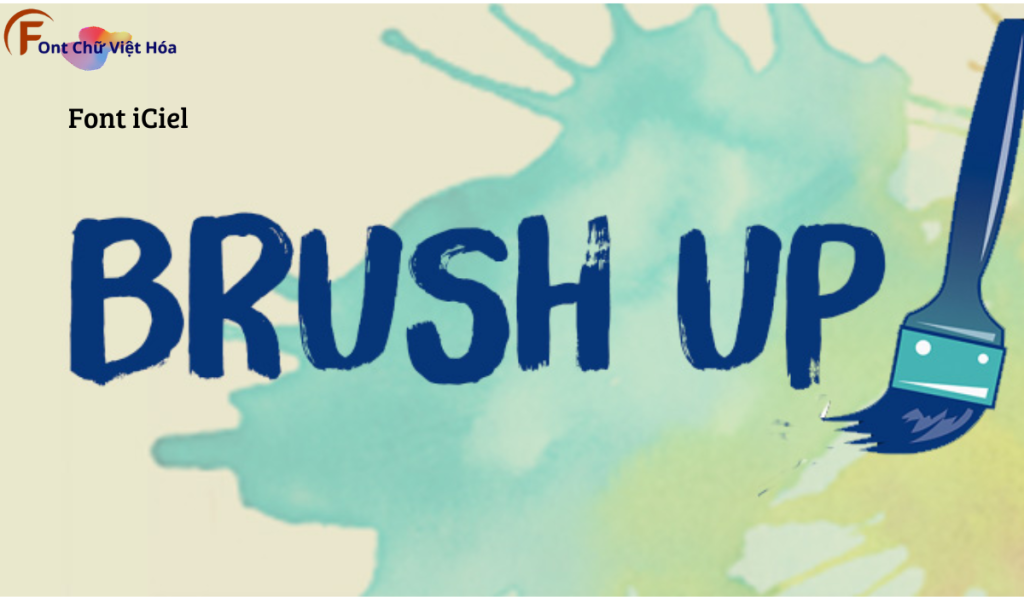
Font iCiel Brush Up Việt Hóa
Tác giả: iCiel Brush Up
Bộ Font: iCiel
Kiểu chữ: Chữ thảo
Font iCiel Brush Up Việt Hóa, thuộc bộ font iCiel, là font chữ thảo hiện đại, nổi bật với các nét chữ vẽ tay độc đáo và độ dày đa dạng. Font này có các đường nét tự nhiên, dễ đọc, tạo cảm giác sáng tạo và nghệ thuật. Font iCiel Brush Up Việt Hóa lý tưởng cho các dự án thiết kế như thiệp mời, bìa sách, và các sản phẩm thủ công. Việc Việt hóa font giúp người dùng dễ dàng tích hợp vào các thiết kế tiếng Việt, mang lại sự tiện lợi và nâng cao tính thẩm mỹ.